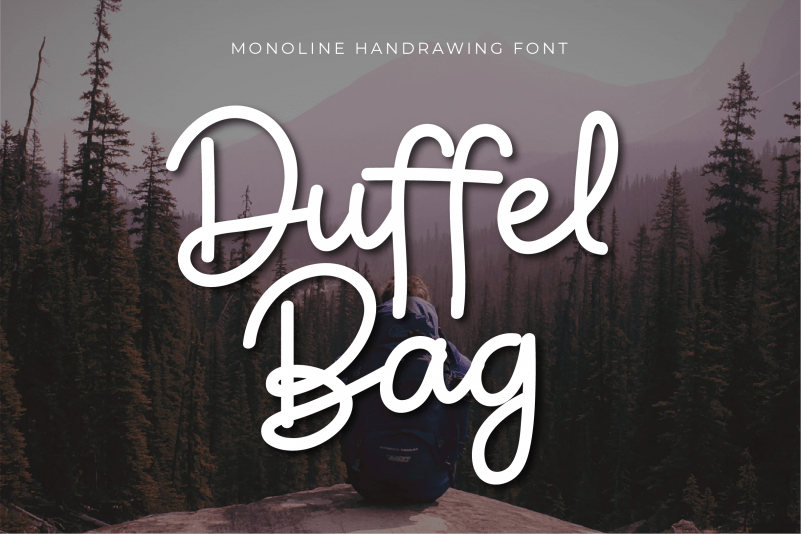
Duffel Bag Script Font – Download Grátis
A Duffel Bag Script Font é uma fonte escrita a mão, moderna e cuidadosamente criada para se tornar seu próximo favorito. Ela captura o charme descontraído de um caderninho casual, fazendo com que seu estilo seja suavemente natural e leitura fácil, enquanto mantém uma versatilidade incrível. Esta fonte brilha em qualquer contexto, independente do tipo de fundo ou se estiver sendo usada sozinha como um título chamativo. Ideal para designers digitais, publicitários e profissionais de marketing que desejam dar um toque pessoal a seus trabalhos, essa fonte é perfeita para projetos que exijem uma combinação suave entre elegância moderna e estilo autêntico. Desenvolvida pela designer twinletter, esta fonte não apenas oferece versatilidade para criar texturas de fundo vibrantes ou títulos chamativos, mas também é ideal para aplicar em diversos canais de marketing digital, desde redes sociais até materiais impressos. Sua simplicidade e versão elegante tornam-a uma escolha inegável para aqueles que desejam incorporar elementos únicos em suas criações, mantendo sempre um equilíbrio perfeito entre a estética moderna e o charme tradicional da escrita a mão.